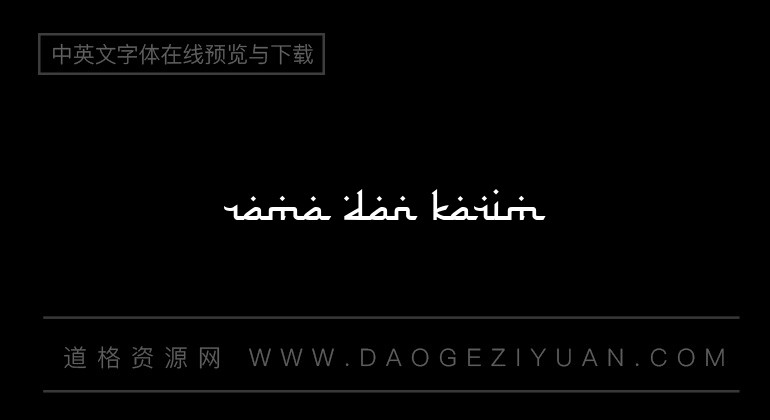
Rama dan Karim
Rama dan Karim 字体是一种阿拉伯文书法字体,也被称为Ruq'ah字体。它是一种流畅、简单、优美的书法字体,常用于书写信件、卡片、宣传品等。Rama dan Karim 字体是阿拉伯文书法中最古老的字体之一,它的原始形式可以追溯到7世纪。这种字体通常用于书写短文本,如标题、名字、证书等。 它是一种具有历史意义的字体,也是阿拉伯文书法艺术的重要组成部分。
Rama dan Karim是一款非常不错的手写艺术字体,具有很好的视觉感,适合于文化类的宣传设计、商业类品牌的广告和产品包装设计以及个性化文字排版等较多场景。
Rama dan Karim字符映射图